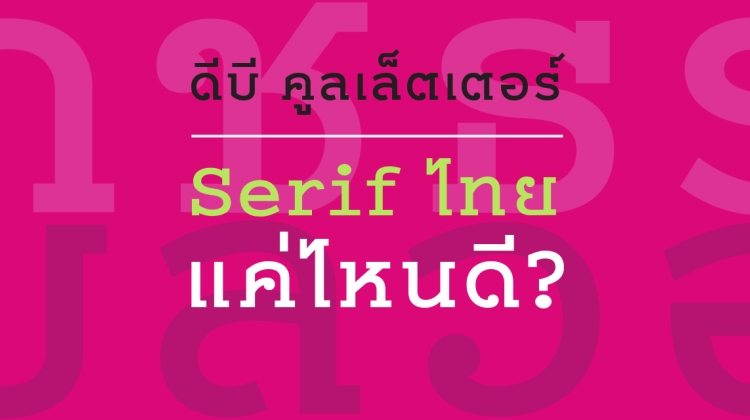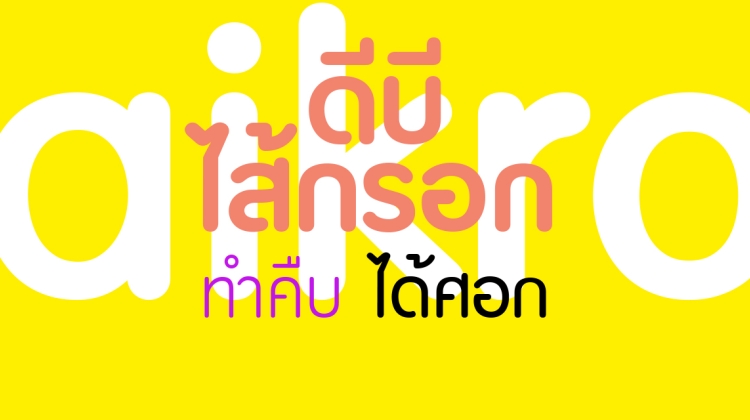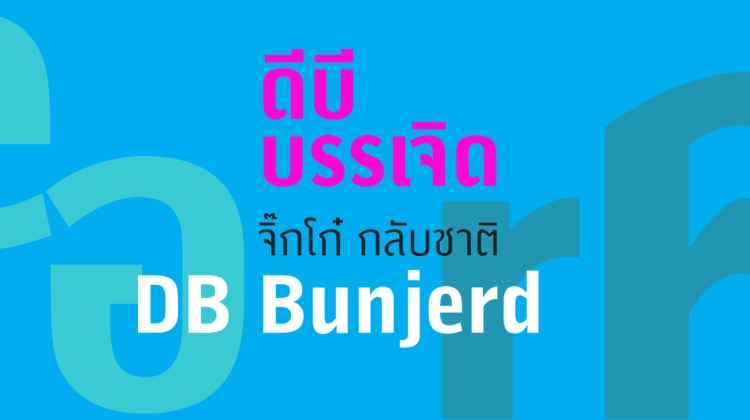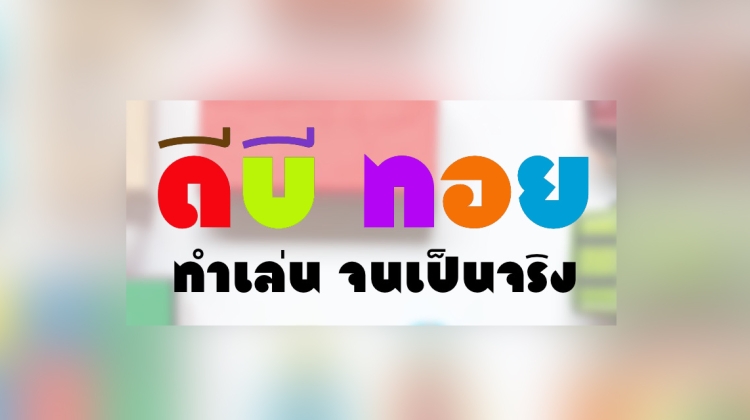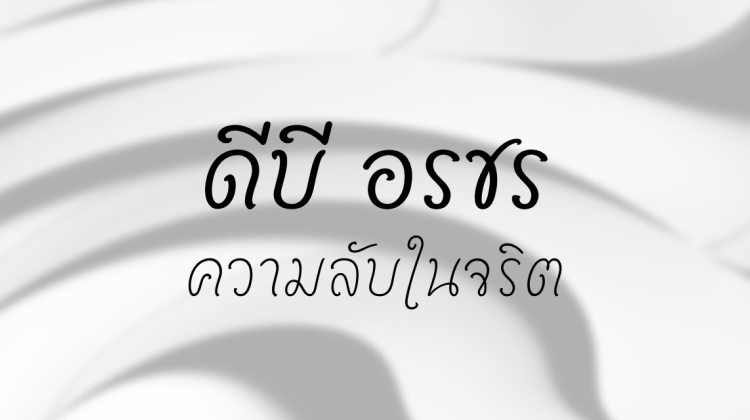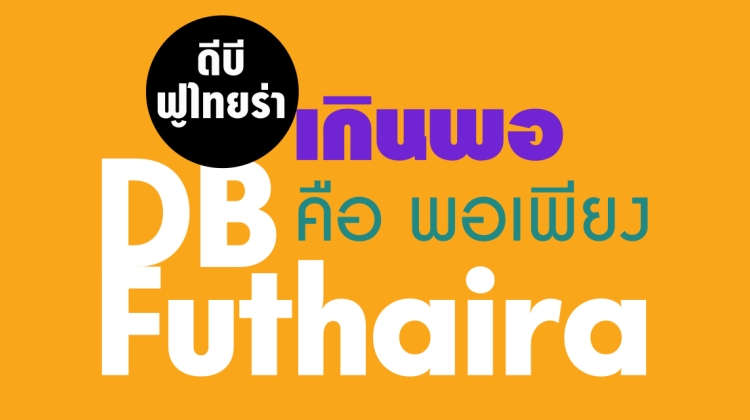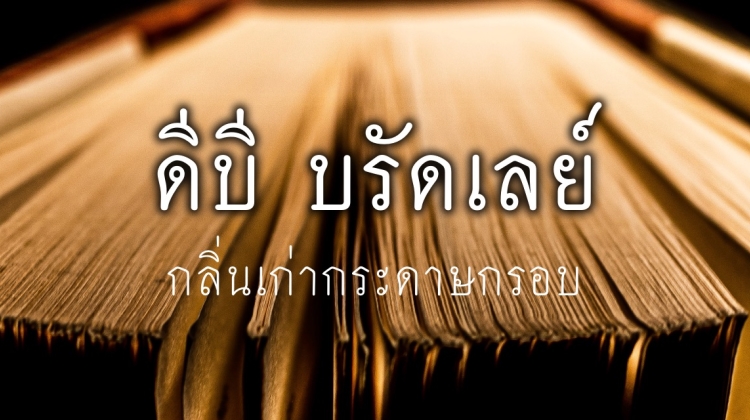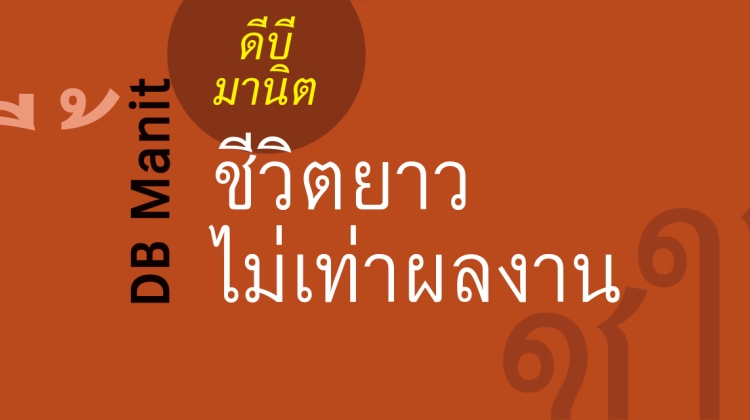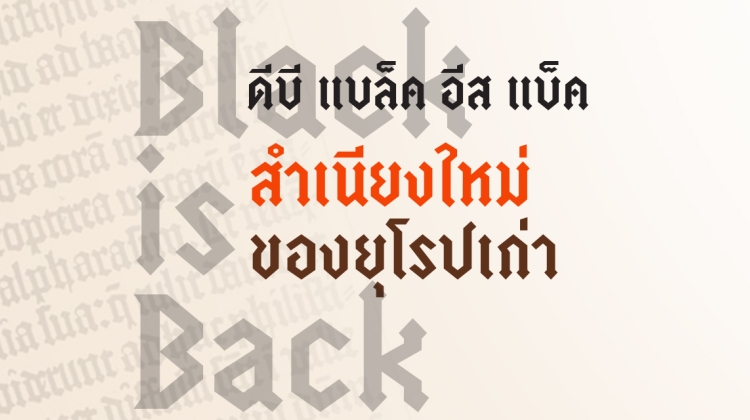
DB Seri
เป็นฟอนต์ไทยเสมือนโรมัน ที่อาศัยเค้าโครงของฟอนต์ Serif Gothic มาปรุงแต่ง
DB Chidlom
เป็นฟอนต์พาดหัวไทย ที่หยิบยืมแบบอย่างตัวอักษรประดิษฐ์ของช่างเขียนยุคอดีตมาทำใหม่ให้ร่วมสมัย
DB Black is Back
เป็นการรื้อสไตล์แบบตัวพิมพ์ Blackletter ที่ปรากฎบนคัมภีร์ไบเบิลในปี ค.ศ. 1455 มาทำใหม่ให้ดูร่วมสมัย
DB Bangrak
งานอนุรักษ์แบบตัวเรียงพิมพ์ตะกั่วคลาสิค ที่มีชื่อเรียกตามรูปลักษณ์ของมันว่า ‘โป้งบาง’
DB Manit
เป็นงานอนุรักษ์ชุดตัวเรียงพิมพ์ตะกั่วไทยในยุคปลายที่มีการเดินเส้นสวยงามสะอาดเป็นเอกลักษณ์ อย่างตัวเขียนไทย
DB Bradley
เป็นงานอนุรักษ์แบบตัวพิมพ์ตะกั่วยุคปลายที่ได้รับอิทธิพลจากตัวพิมพ์ยุคแรกของคุณหมอบลัดเลย์ (Dan Beach Bradley) ซึ่งมี ๒ แบบ คือ แบบเหลี่ยม (Angular) และแบบโค้ง (Curved).
DB Futhaira
เป็นฟอนต์ที่ออกแบบขึ้นโดยการนำข้อดีของแบบอักษรลอกไทยที่นับว่าใกล้เคียงฟอนต์ Futura ที่สุดมาปรับปรุงใหม่.
DB Orrachorn
คือฟอนต์ไทยแบบลายมือเขียนที่ ‘ปรุงจิต’ เข้าไปให้เส้นดูพริ้วหวาน
DB Toy
เป็นฟอนต์ดิสเพลย์ไทยที่ทำขึ้นด้วยอารมณ์สนุก จากความทรงจำเมื่อครั้งแรกที่ได้เห็นแบบตัวอักษร Baby Teeth ในอดีต และตื่นตากับรูปทรงเรขาคณิตหนาทึบที่น่ารักของมัน
DB Bunjerd
คือการถือกำเนิดใหม่ของฟอนต์ไทยเชื้อสาย sans serif อมตะของฝรั่ง ด้วยน้ำหนักตัวพิมพ์ที่มีให้เลือกใช้เหลือเฟือ และแบบอักษรลาตินที่ปรับปรุงใหม่หมดทั้งชุดให้ ‘บรรเจิด’ กว่าเดิม.
DB SaiKrok
คือฟอนต์ตัวพาดหัวของไทยที่เทียบเคียงได้กับฟอนต์ VAG Rounded กล่าวคือเส้นมีน้ำหนักสม่ำเสมอกันและหัวท้ายมนคล้ายไส้กรอก.
DB CoolLetter
เป็นตัวพาดหัวไทยที่ดัดแปลงมาจากตัวพมพ์ดีดฝรั่งชื่อ Courier โดยปรับปรุงช่องไฟเดิมแบบ monospaced font เสียใหม่ เพื่อกระจายน้ำหนักอักษรให้สวยงามขึ้น.